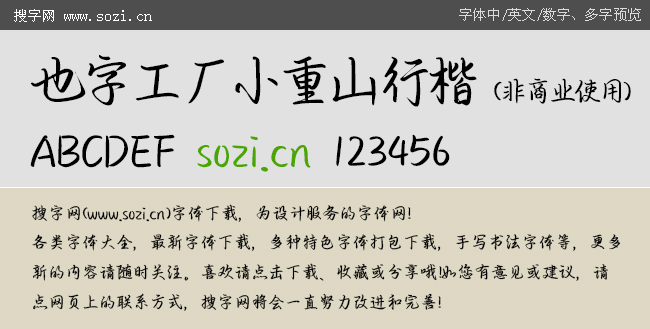
也字工廠小重山行楷
搜字網(wǎng)給大家提供一款也字工廠小重山行楷(非商業(yè)使用)中文字體下載,也字工廠小重山行楷是一款手寫書法字體,字體筆觸纖細(xì),書寫自然流暢,字形瀟灑大方。適合應(yīng)用于書籍、海報(bào)、網(wǎng)頁(yè)設(shè)計(jì)等應(yīng)用(此字體為個(gè)人非商用版,商用可以聯(lián)系:官方網(wǎng)址:https://yefont.com/home,聯(lián)系方式:13798980448)。